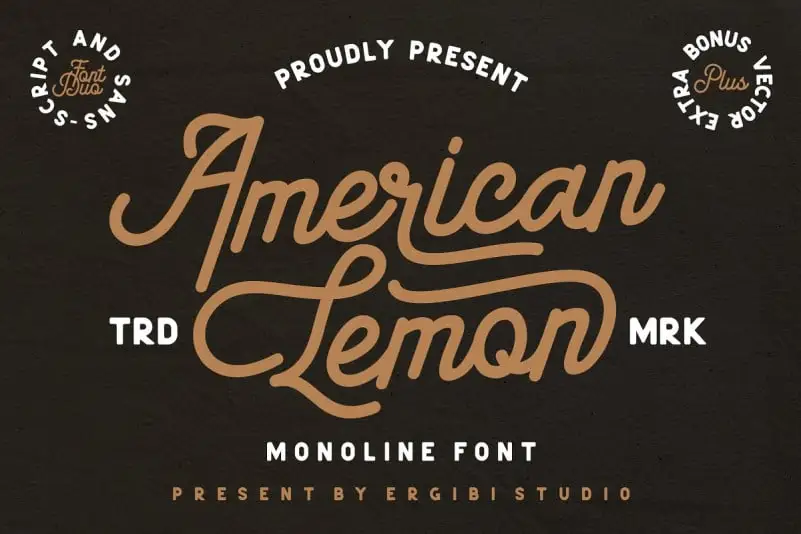
American Lemon Font Duo – Download Grátis
Aqui está uma descrição em português para a página de download da fonte “American Lemon Font Duo”, seguindo os requisitos fornecidos: Esta é uma duo de fóntes script monoline, desenvolvida pela M.0Type. Ela é um tipo moderno de script que vem perfeitamente complementado por uma sans-serif. Ambas as fóruns – o script e a sans-serif – se combinam perfeitamente, tornando-a ótima para aplicações variadas como logotipos, roupas, marcações, embalagens, anúncios e muito mais. A fonte “American Lemon Font Duo” vem em letras maiúsculas e minúsculas, símbolos e números, alternâncias de estilo, ligações e ponteiros finais. Também suporta multilínguas. O final do swash faz com que a fóntes esteja completa e o tamanho varia para facilitar o acesso ao final do swash. Com essa fonte à sua disposição, você pode criar uma experiência visual única em logotipos e identidade visual, adorando cada detalhe na forma dos símbolos e números. Estas fóntes são ideais para designers que desejam dar um toque especial a seus projetos de arte digital ou impressa. Ela é perfeita para aqueles buscando uma combinação elegante, sem perder o encanto do script.